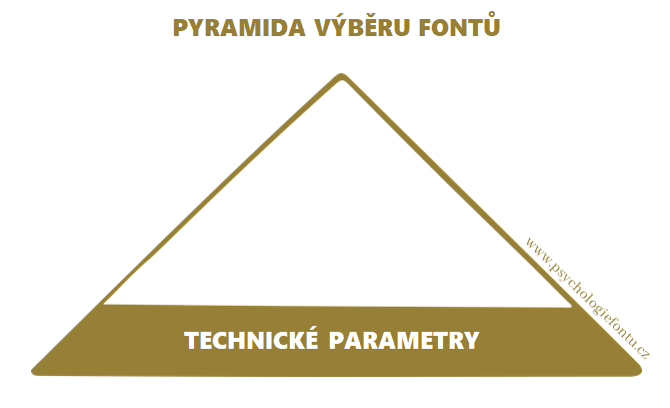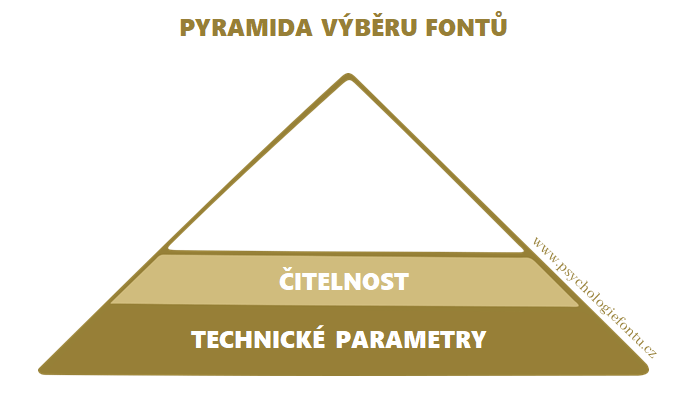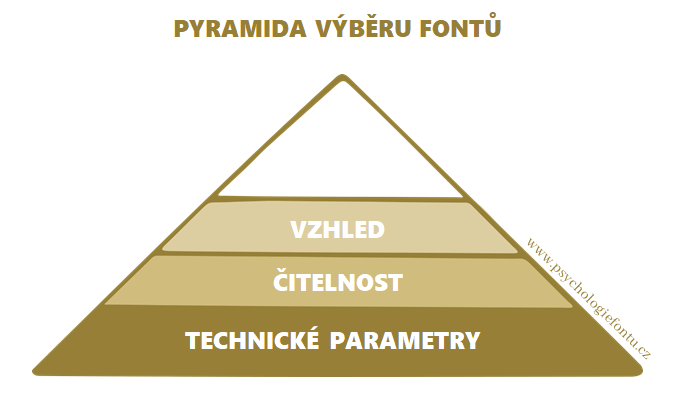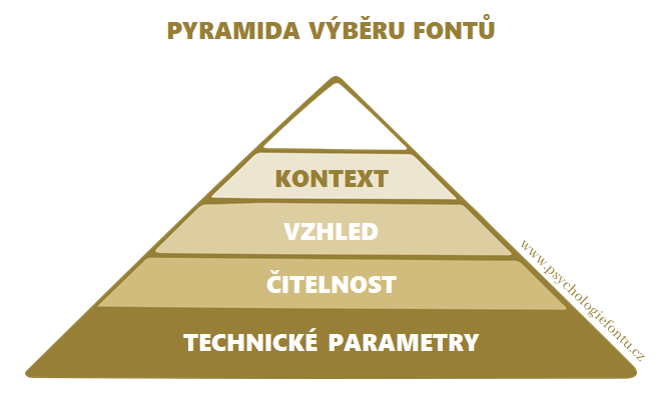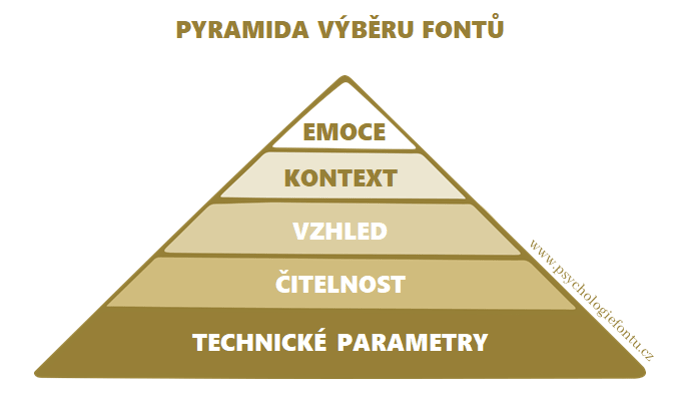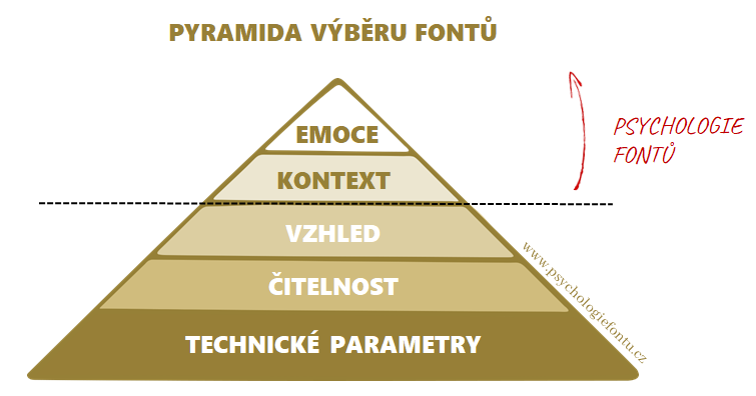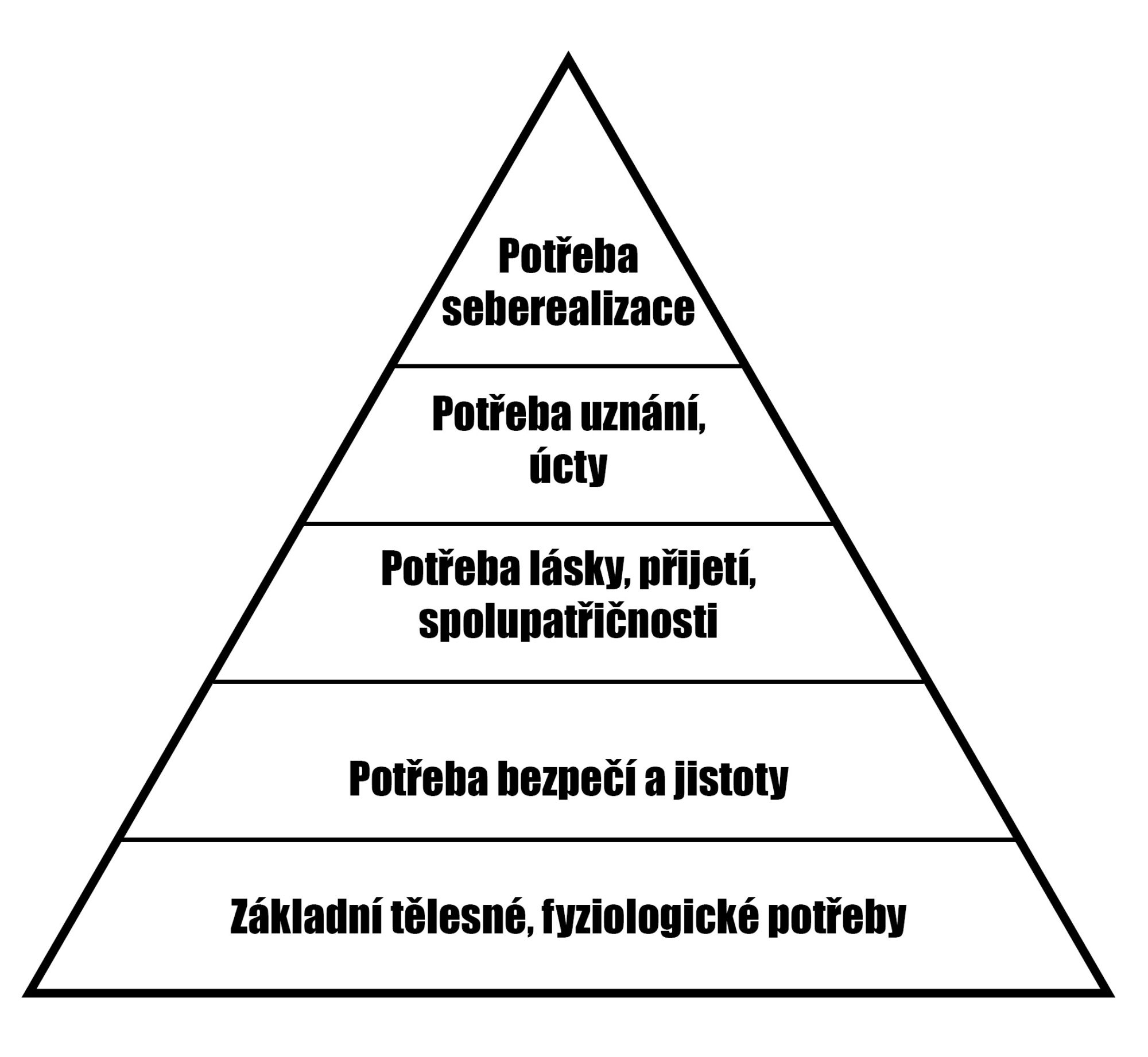
Co je důležité při výběru fontu? Záleží víc na rychlosti načítání, čitelnosti anebo vzhledu písma? Čím začít, přes jaké kritérium při výběru fontu nejede vlak a co nejvíce ovlivní konverze? Jakou roli při výběru fontu hraje subjektivní estetický vkus?
Vždy jsem trošku tápala, když se mě někdo zeptal: „A proč bych se měl zabývat psychologií fontů, důležité je přece hlavně, aby text byl typograficky správně a čitelný.“ A bezesporu měla dotyčná osoba pravdu, když se text špatně čte, žádná psychologie situaci nezachrání. Ale přesto jsem jsi byla jistá, že má svou velkou roli, jenom jsem to nedovedla srozumitelně a logicky vysvětlit.
Až v jednu bezesnou noc jsem na to přišla. Také vás geniální nápady přepadají ve čtyři ráno?
Lidé se nejlépe učí na základě paralel, něčeho, co dobře znají. Pokud se jim podaří paralelu aplikovat na něco nového, nepopsaného, novinku pochopí daleko snáz. A tak pro odpověď na otázku: „Proč bych se měl zabývat psychologií fontů, nestačí, že je text čitelný a správně?“ půjdeme od lesa. Tedy vlastně od pyramidy. Pyramidy pana Maslowa. Asi ji znáte všichni:
MASLOWOVA PYRAMIDA POTŘEB
5 úrovní základních lidských potřeb, seřazených od životně důležitých až po takové, bez jejichž naplnění přežijeme. Kvalita života se s každou úrovní pyramidy zvyšuje.
To, na které úrovni se zastavíme, záleží na nás, situaci, ve které se nacházíme, na našem charakteru a potřebách.
Někdo se bez seberealizace úplně obejde a nechápe, jak pro druhého může být důležitější, než teplé bydlo. Jsou lidé, kteří žijí pro druhé a jsou závislí na jejich přijetí a pak jiní, kteří jdou bez problémů sami proti proudu.
A stejné je to u fontů.
Stejně jako člověk, ani písmo nemusí zůstat jen u základních potřeb. Může jich plnit daleko více, záleží, jak jste nároční a co od textu čekáte. Možná vám stačí mít plné břicho a možná potřebujete zažívat pocit, že měníte svět. Přeloženo do výběru písma – možná vám stačí, že je čitelné a možná chcete takové, kterým cíleně oslovíte lidi, kteří od vás rádi nakoupí.
Vytvořila jsem pro vás Pyramidu výběru fontů, pojďme se na ni podívat.
1. Patro
TECHNICKÉ PARAMETRY
Vše, co písmo musí mít, abychom ho dostali tam, kam potřebujeme. Když ho máte v *.ttf nebo *.otf souboru a vaše šablona umožní import pouze z Google fontů, tak ho do H1 nedostanete, ani kdybyste se rozkrájeli. Pokud máte e-shop, většinou vám umožní vybírat z velmi omezeného počtu fontů, ale stojí za to si zjistit, jestli si vlastní font nemůžete nahrát za příplatek. Pokud připravujete obrázky na sociální sítě v Canvě, potřebujete mít font v Canvě. Atd.
Pokud si umíte poradit přes HTML, máte výhodu.
Nemožnost nahrát font na web nebo do jakékoli aplikace nemusí být pouze technického rázu, ale také otázka licencí. Font, stejně tak jako třeba fotky, podléhá autorskému právu a pokud nemáte licenci, která vám umožní jeho použití pro komerční účely, máte smůlu.
U webů sem spadá i rychlost načítání na web – jsou weby, pro které je každá milisekunda důležitá. Každý font a řez navíc web zpomaluje, i když s použitím variable fontů se blýská na lepší časy.
Prostě první patro je základ, neoddiskutovatelný a nerozporovatelný. Musí fungovat.
2. Patro
ČITELNOST
Když už font dostaneme tam, kde ho chceme mít (a legálně), čitelnost je pro jeho použití naprosto zásadní. Obzvlášť, pokud se jedná o písmo v delších větách a odstavcích textu.
Do tohoto patra spadá:
- jaký má tvar a řez,
- jakou má velikost a kolik znaků na řádku,
- jaké je použité řádkování, zarovnání, zvýraznění,
- jestli font umí česky,
- Jestli má tu správnou barvu – nejde o to, jestli je černý nebo bílý, ale jestli je dostatečně kontrastní proti pozadí.
Vyčerpávající článek na téma čitelnost najdete tady.
3. Patro
VZHLED
Aneb líbí/nelíbí. Ano, přiznejme si to, většina lidí vybírá fonty podle toho, jak se jim líbí anebo ještě víc, jak se bude líbit ostatním. Jak často jste viděli někde na internetovém fóru otázku:
„Který font se vám líbí nejvíc?“.
A není to zdaleka přístup jenom amatérů, s tím, jak vybírat písmo a nebýt ovlivněný osobním vkusem bojují i méně zkušení grafici a webdesignéři, pokud nemají buď vzdělání, nebo estetické cítění, doplněné zkušenostmi z praxe. Na internetu najdete spousta článků, jaké písmo je trendy anebo zaručené tipy na kombinace fontů, „které fungují“.
Profíci zkušení anebo vybaveni estetickým cítěním se psychologií fontů podvědomě řídí. Ví, že „hezký“ font nestačí, protože písmo má plnit úplně jiné funkce, než aby bylo jenom hezké a líbilo se, takže při práci intuitivně berou v úvahu daleko více parametrů, než pouze subjektivní pocity a vnímání.
Vzhled má přímou souvislost s čitelností, takže je rozhodně důležitý. Měl by ladit s celkovou prezentací textu, s vizuální identitou značky, s fotkami, ilustracemi, ikonami… Takové to, že když se na text podíváte, nenapadne vás hodnotit font, protože je vše v pořádku a harmonii.
Prostě to ladí.